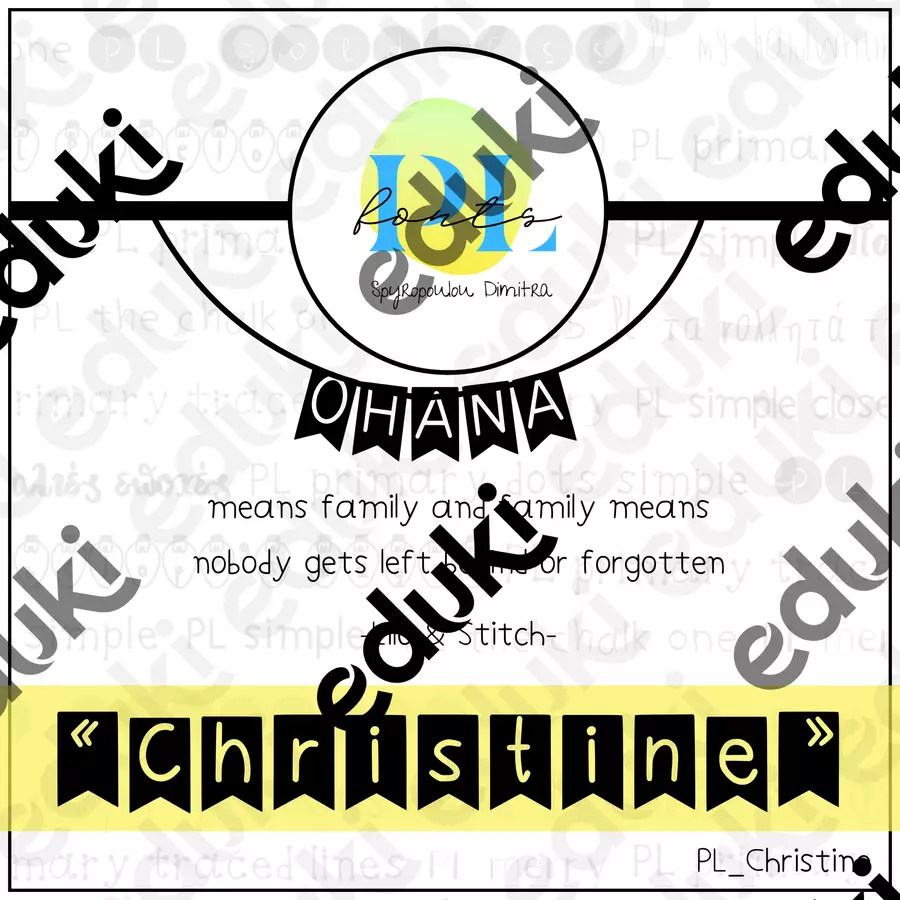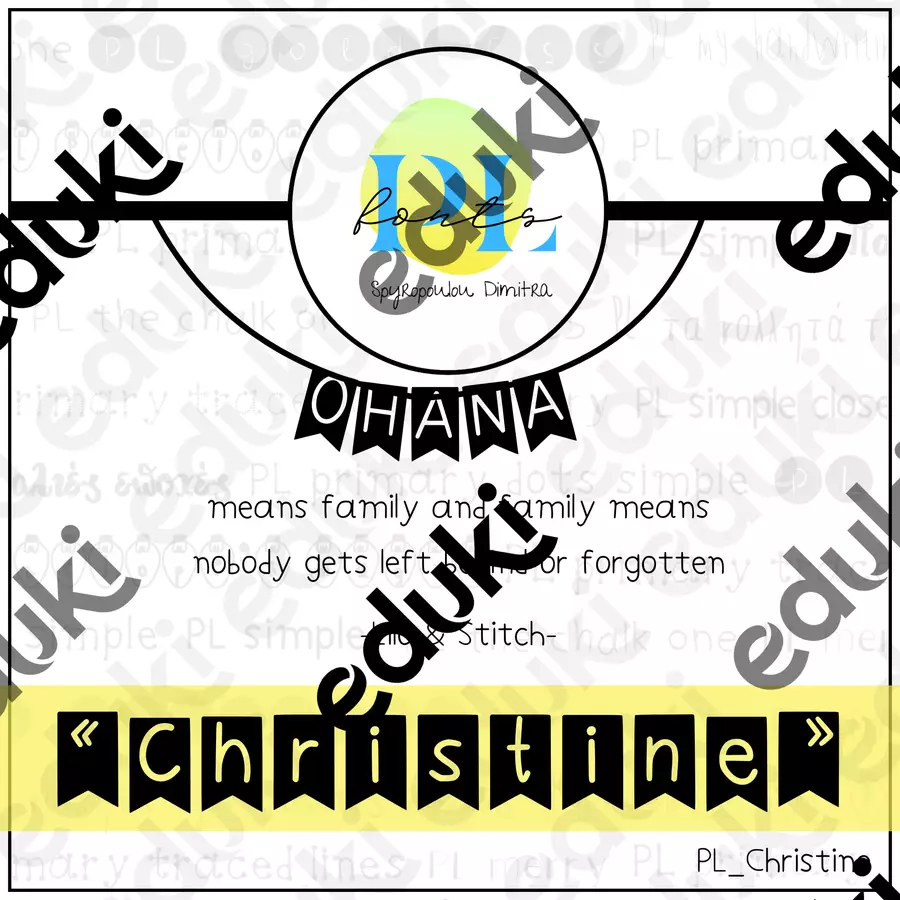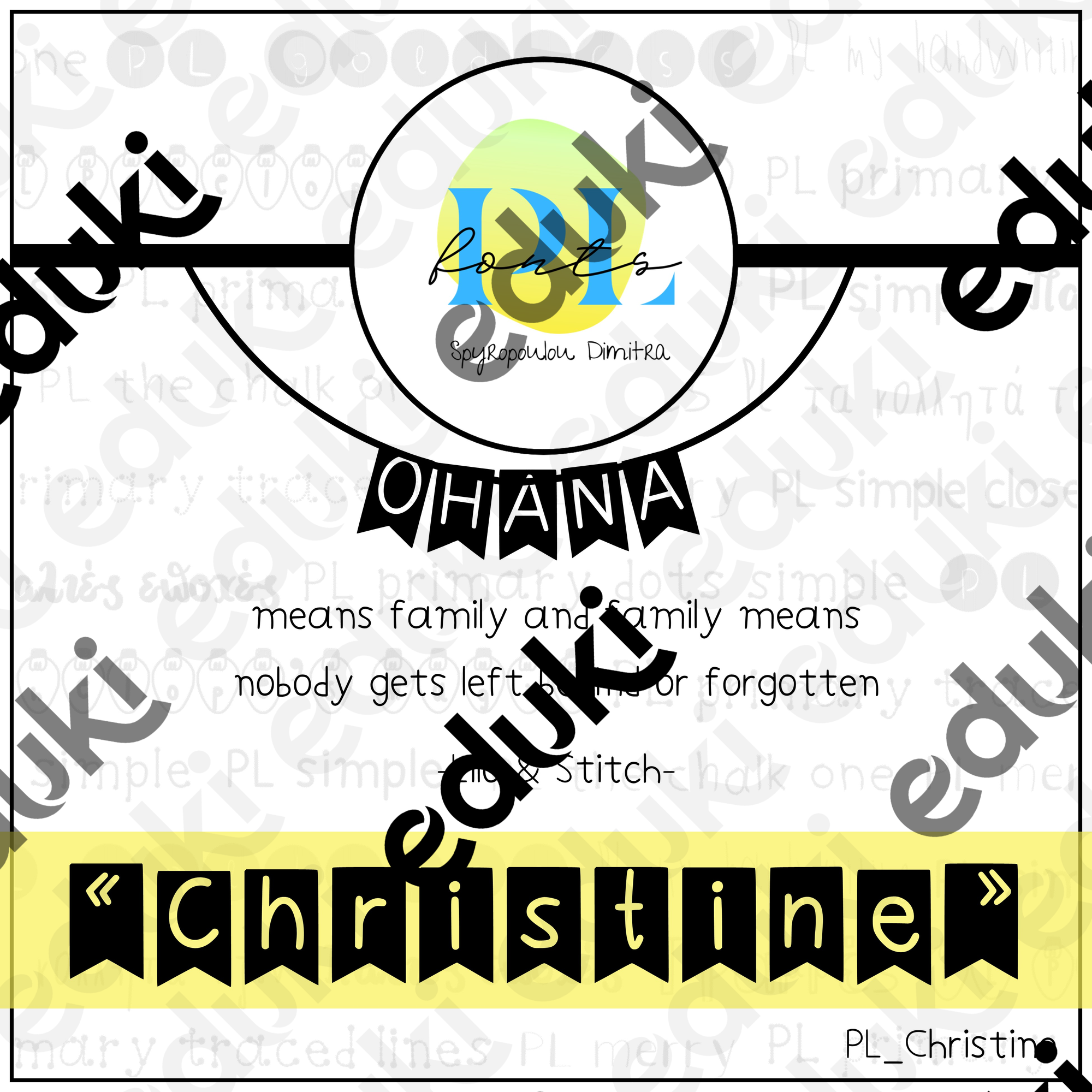
Αυτή η γραμματοσειρά ονομάζεται "Christine" και αποτελεί γραμματοσειρά τίτλων (script font). Τα γράμματα βρίσκονται μέσα σε σημειάκια. Να θυμάστε πως όταν αλλάζετε χρώμα στην γραμματοσειρά αλλάζει χρώμα μόνο το μαύρο της στοιχείο (το σημαιάκι) και το γράμμα (άσπρο χρώμα) μένει διάφανο.
Η γραμματοσειρά περιλαμβάνει ελληνικούς ΚΑΙ αγγλικούς χαρακτήρες, αριθμούς, μαθηματικά σύμβολα και σημεία στίξης.
This font is called "Christine" and it's a script font. The letters are drawn on flags. Please remember that when you change the color of the font, only the black part of it, the flag, with change color. The white parts (the letters) are transparent.
This font includes Greek and English characters, numbers, mathematical symbols, and punctuation marks.